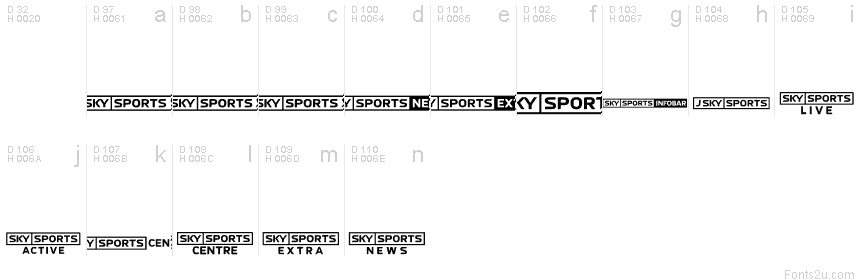
SKYfontsport od mdtaDESIGN je bezplatné techno display písmo s údernou sportovní estetikou televizních grafik z přelomu 90. a 2000. let. Písmena jsou široká, zaoblená a precizně zpracovaná; kombinace jemných rohů a ostrých řezů dodává slovům dynamický, kompaktní a technický výraz, který nepůsobí příliš uhlazeně.
Přirozeně zapadne do sportovního brandingu, e-sportových bannerů, televizních titulků, plakátů k akcím nebo krátkých nadpisů, kde toto bezplatné písmo potřebuje dodat ten nezaměnitelný televizní nádech. Díky čtvercovým křivkám a ostrým řezům funguje skvěle i v logách týmů nebo v krátkých titulcích, protože i pár písmen v sobě nese ten správný odvážný on-air rytmus.